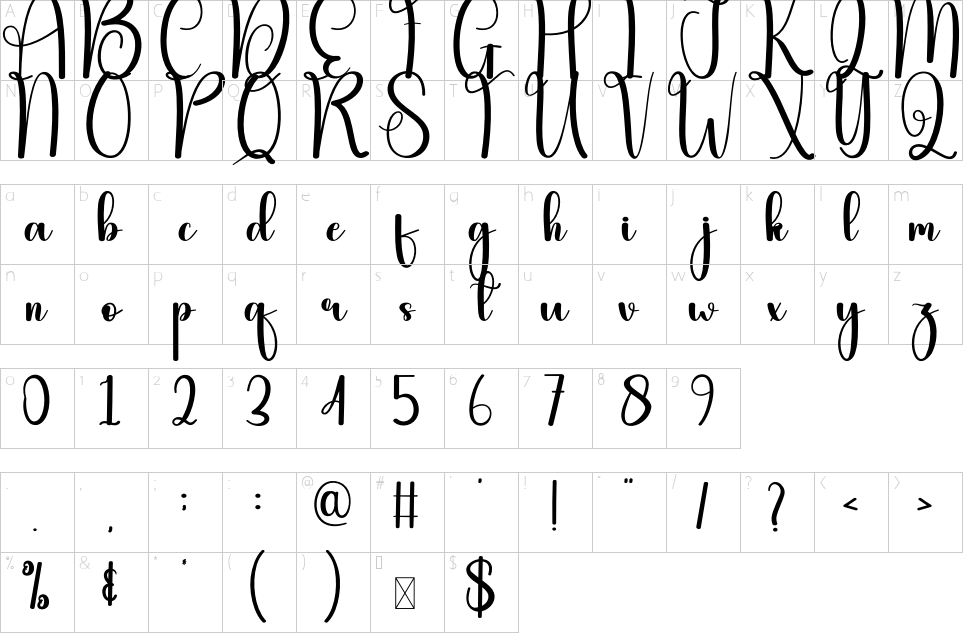
Descubra uma fonte gratuita e versátil na categoria de fontes grátis, o Monday Font. Desenvolvido pelo designer desconhecido, esta fonte vem em versões para Windows e Mac e já foi baixada 164 vezes. Ideal para criações de layout web, design gráfico ou qualquer projeto que necessite de uma fonte clara e legível, o Monday Font é uma ótima opção para qualquer designer gráfico, oferecendo uma diversidade de usos e uma experiência de design agradável. Descubra agora e faça seu design brilhar com a Monday Font.